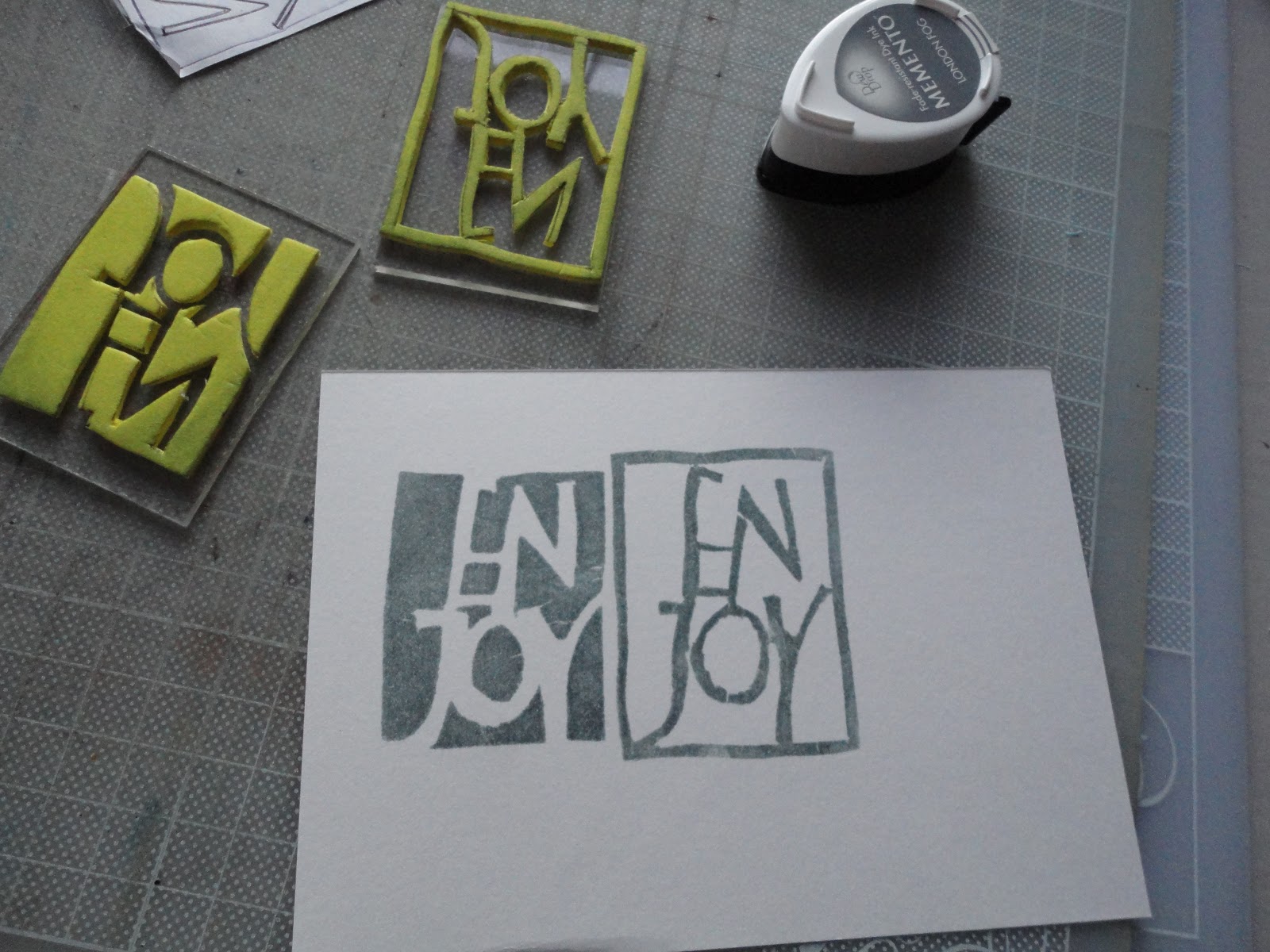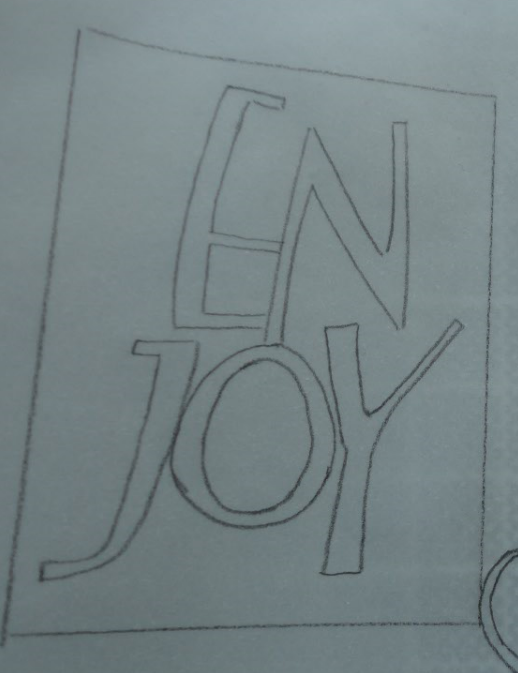
stamp making 2
En we blijven doorgaan met stempelen !
And we keep on stamping !
Op een glazen onderzetter plakte ik allemaal restjes van foam die nog op mijn tafel lagen.
Deze werd dan mijn volgende stempel .
I used the different little pieces of leftover foam from my desk for the next stamp.
Together with a nice new handlettering font, I created the lovely day card.
Stamp number two for today is 'Life', stamped in memento ink, espresso truffle
Stamp number 3 is what I call my Aboroginal foam stamp.
With Adirondack ink bottle and denim and the use of penciln I created this card:
Deze laatste stempel, noem ik de aboriginal stempel. Ik gebruikte Adirondack bottle en denim om mee te stempelen. De tekst is in potlood.
stamp making
Een maand of zo geleden (klik hier ) maakte ik al een paar ontwerpjes voor het maken van eigen woordstempels.
Ik begon vrij simpel met dit woordje uitgekerfd in foam:
About a month ago ( click here ) I started to make a few designs for my word stamps. I started really simple with the word 'van' / from-of
This was my next try: 'gefeliciteerd' - congratulations :
Tweede poging: gefeliciteerd. Meer dan een uur intensief en heel voorzichtig snijden van de letters:
..met een eerder zwak resultaat, als je't mij vraagt. De 'c' is niet zo erg duidelijk en vele andere letters vrij 'verhakkeld'.
But I didn't like the result really. The 'c' is not very legible and some other letters are not very clear either....
Dan probeerde ik eens met een factis-carving block i.p.v. met de foam, bv dit blad
Next I tried with the factis carving block instead of the foam and made a design of this leaf:
Zoals bij voorbeeld in deze kaart :
Like in this card:
En tenslotte maakte ik nog (opnieuw uit foam) een ontwerpje : 'enjoy' :
And from the design 'enjoy',
een positieve én de negatieve tekststempel - the positive and negative word stamp
Behalve deze zelfgemaakte stempels, gebruik ik ook al eens deze (zelf gekochte ) :
Except for these self-made stamps, I also have these (self-bought ones) :